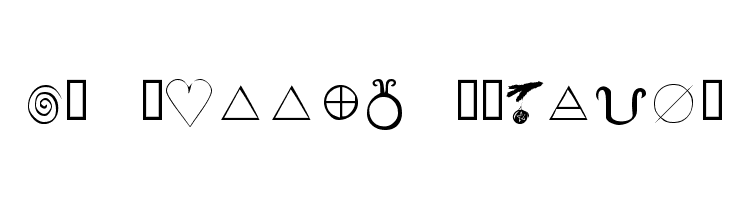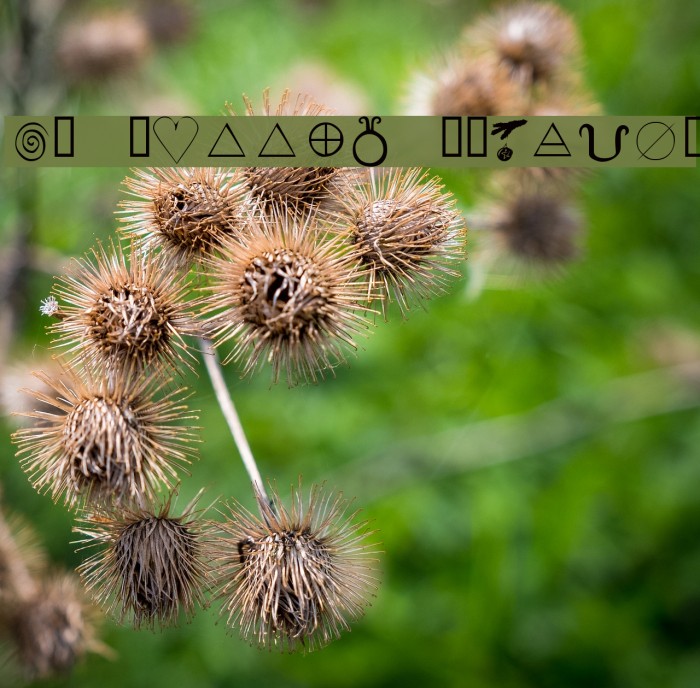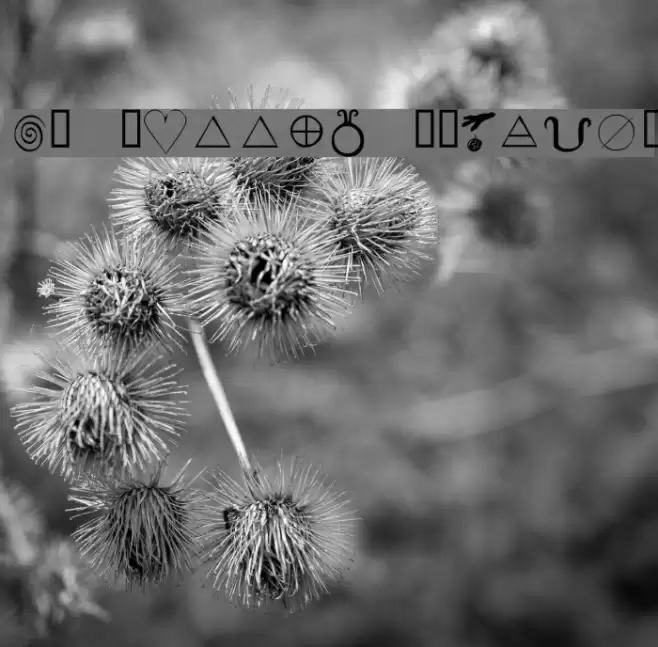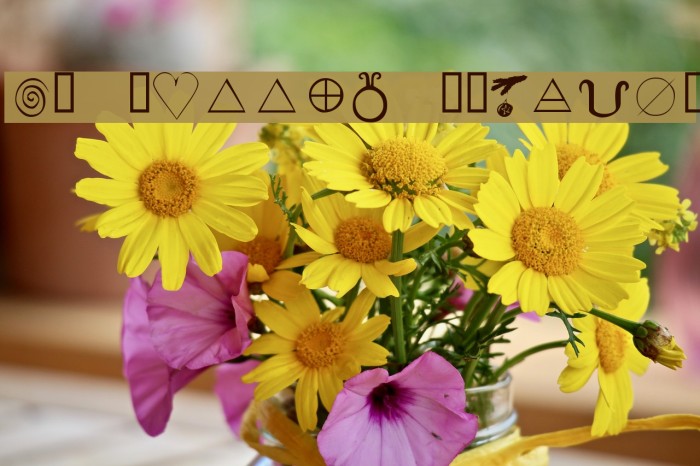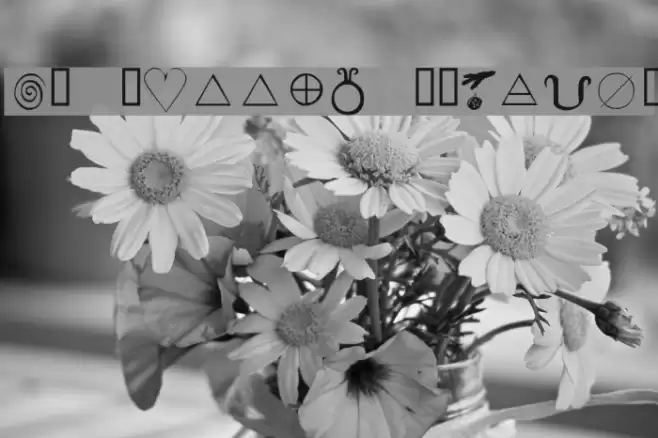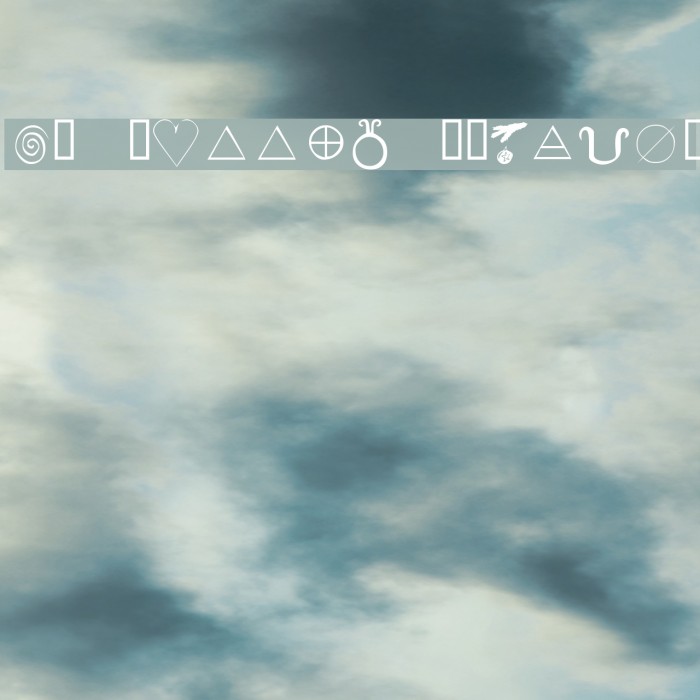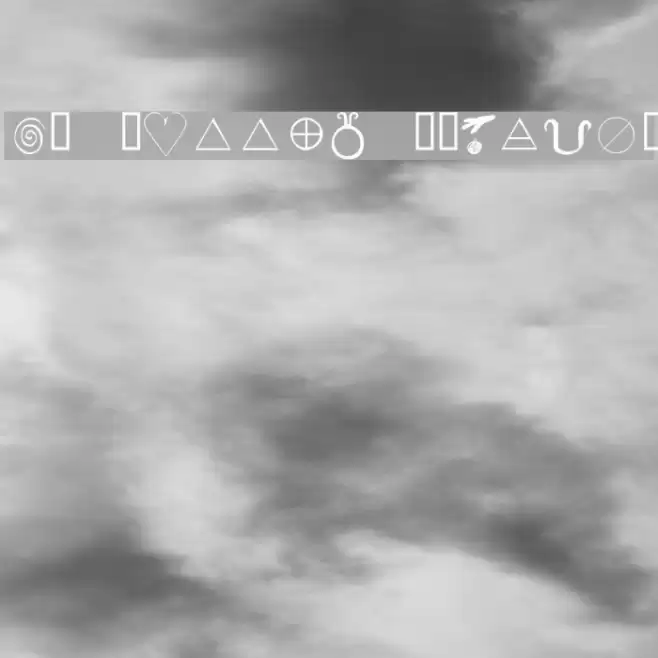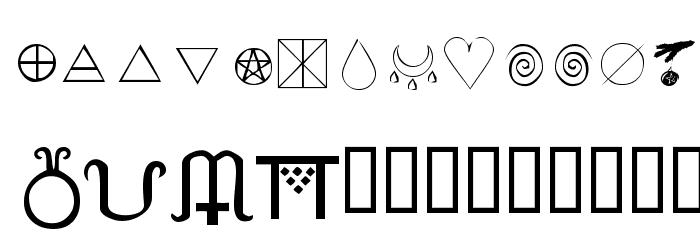
KR Wiccan Symbols Font
| النمط العام | Mystical, Esoteric, Decorative |
| حالة الاستخدام | Decorative elements, Thematic designs |
| مشاريع مقترحة | Ideal for spiritual or mystical-themed projects, such as book covers, posters, or event invitations related to Wiccan or esoteric themes. |